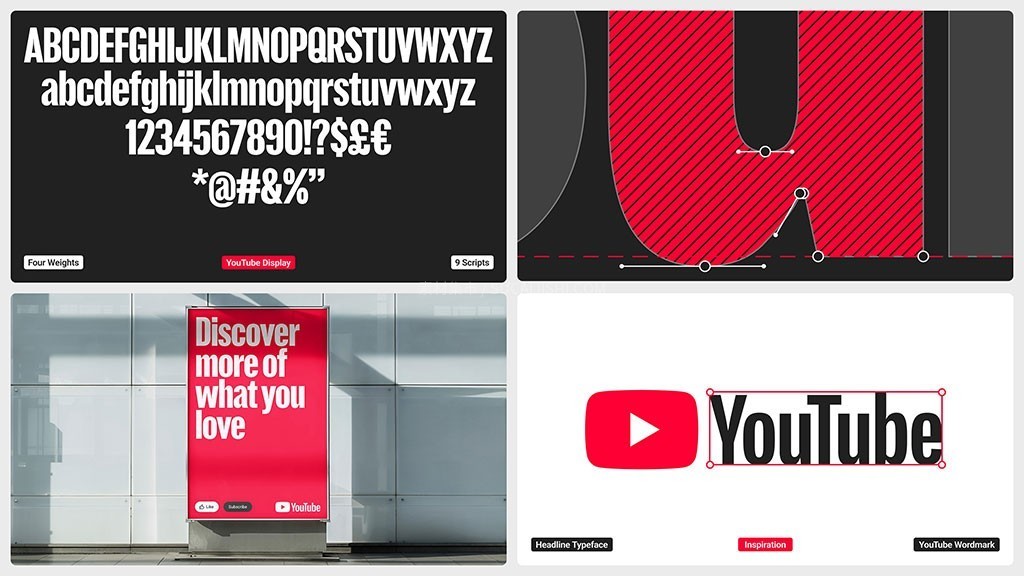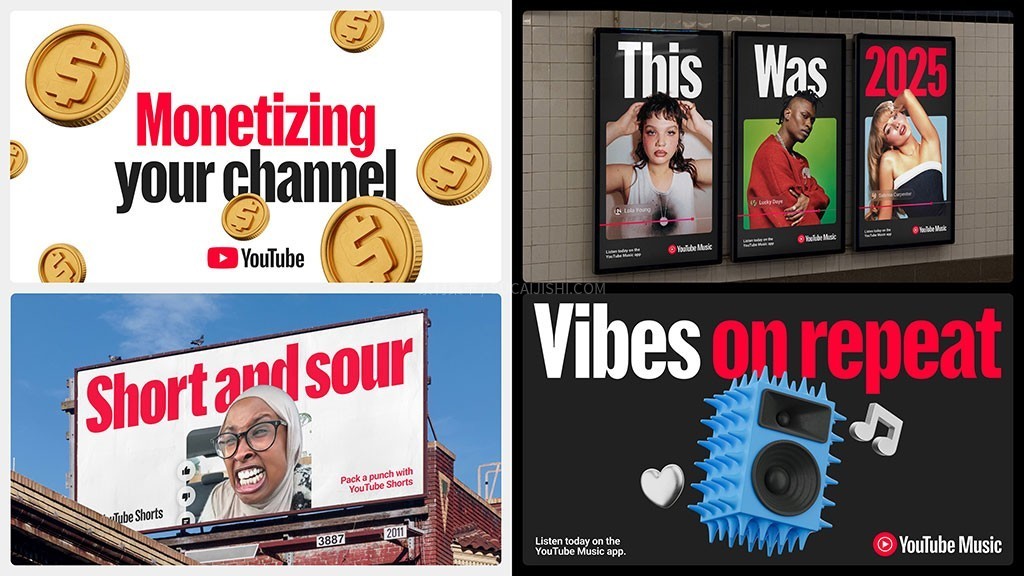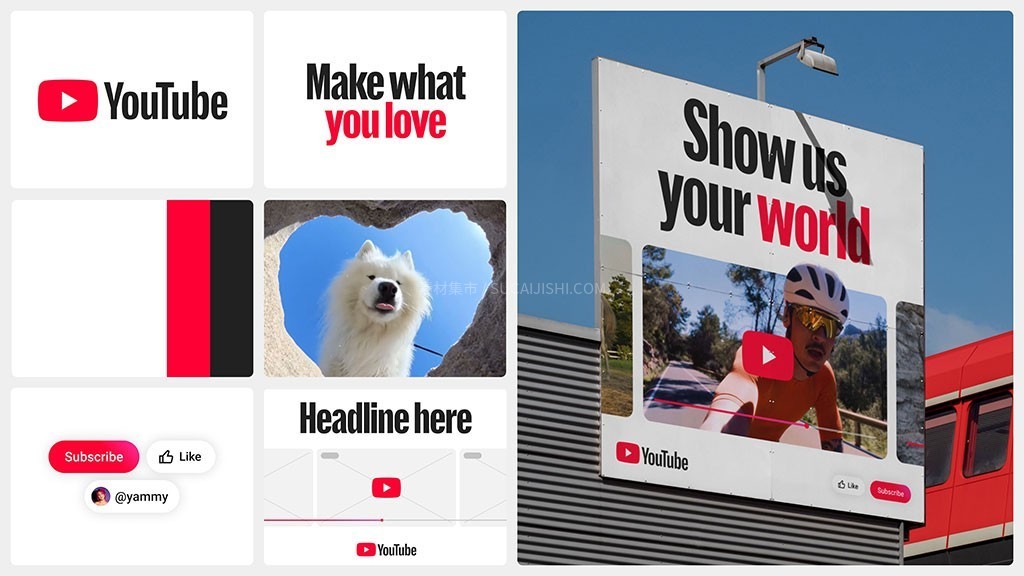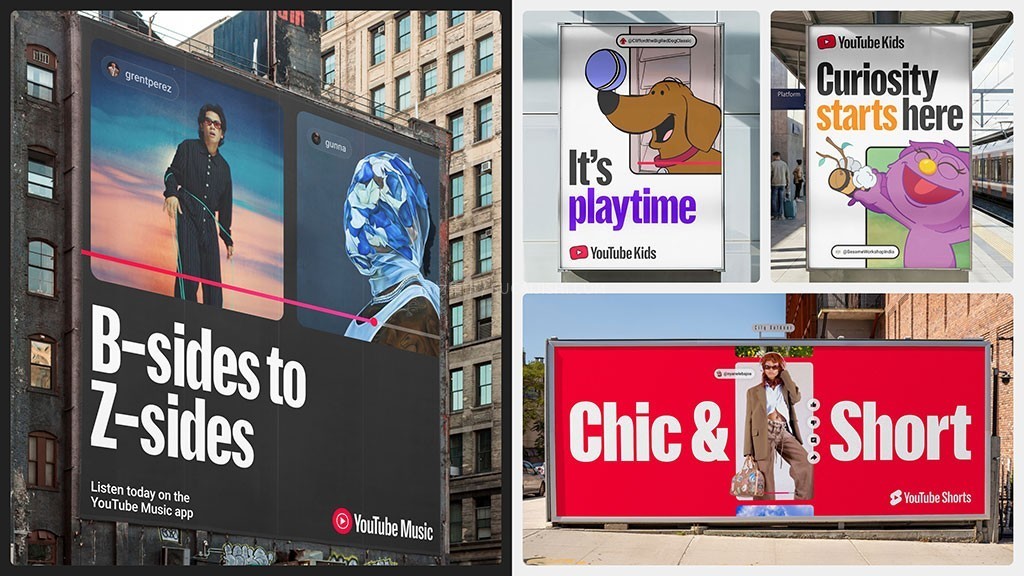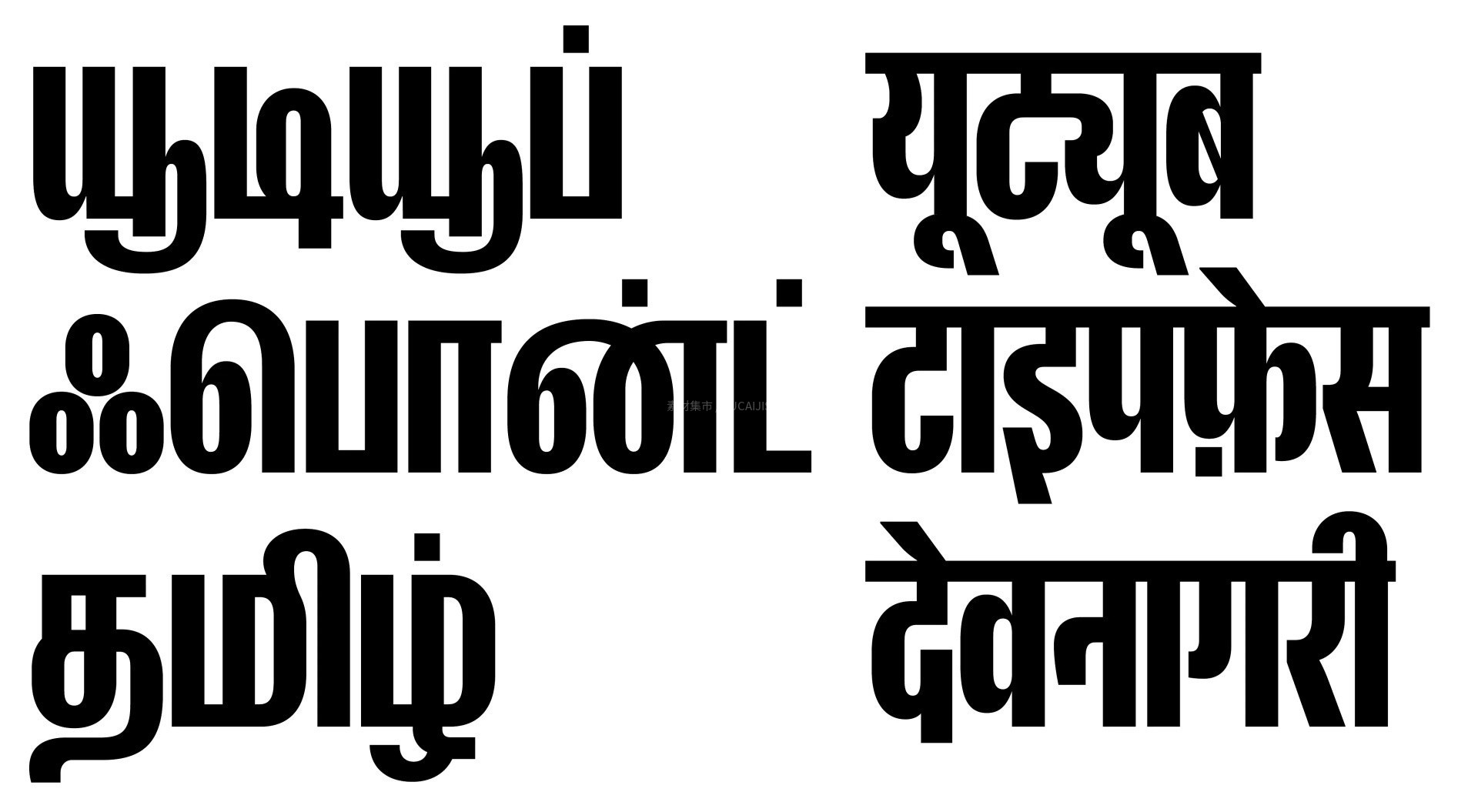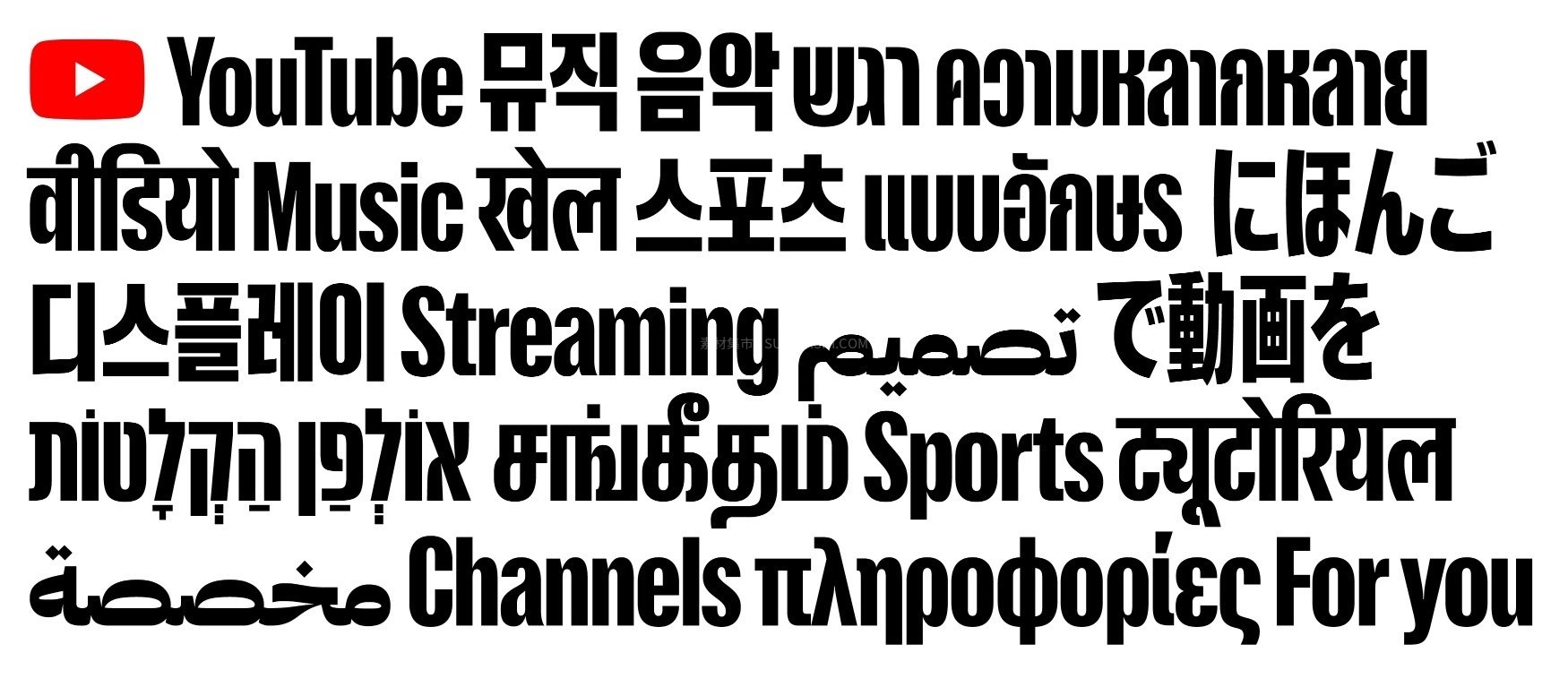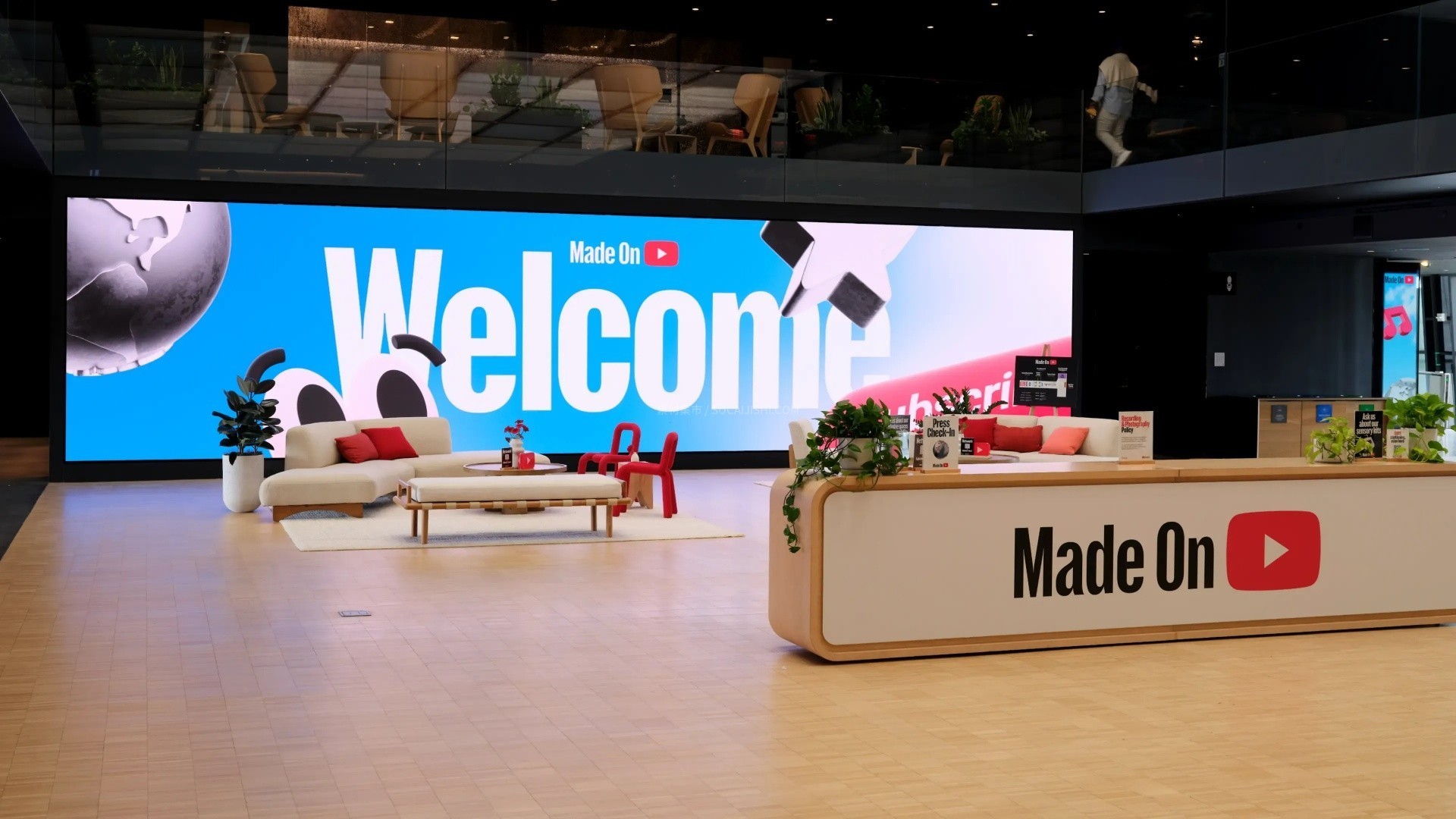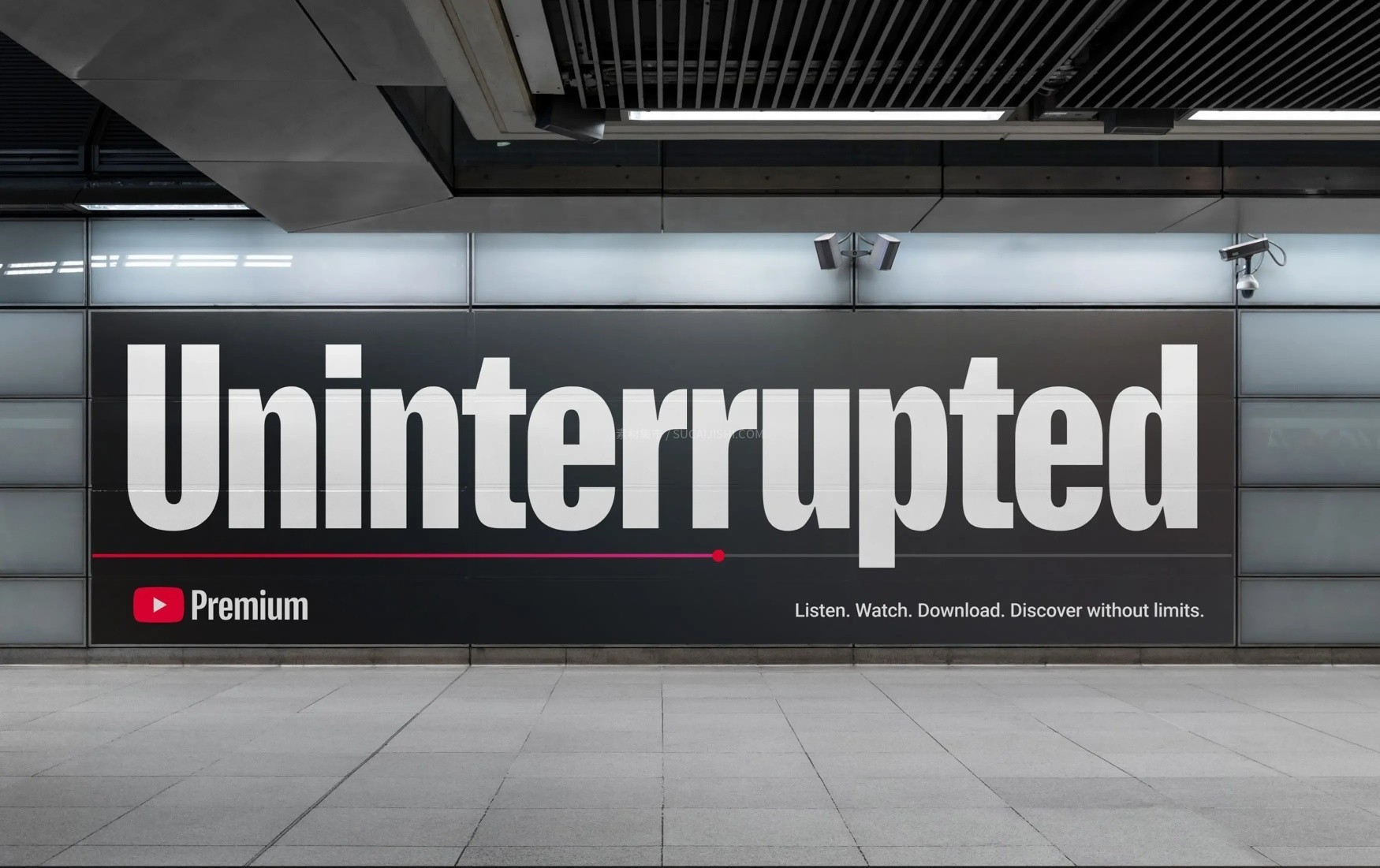
YouTube 官方全球多语言字体完整版
油管(YouTube)全球视觉升级的!这款专门为流媒体巨头量身定制的专属显示字体真的绝了~它一口气包揽了 8 种样式,更硬核的是完美支持天城文、泰米尔文、韩文、泰文、希伯来文、阿拉伯文、日文和泛欧洲语言等 8 大全球主流语系!不仅无死角覆盖了全球数十亿用户的使用场景,还在保持视觉极度一致的同时,拿捏住了油管独特的品牌调性。